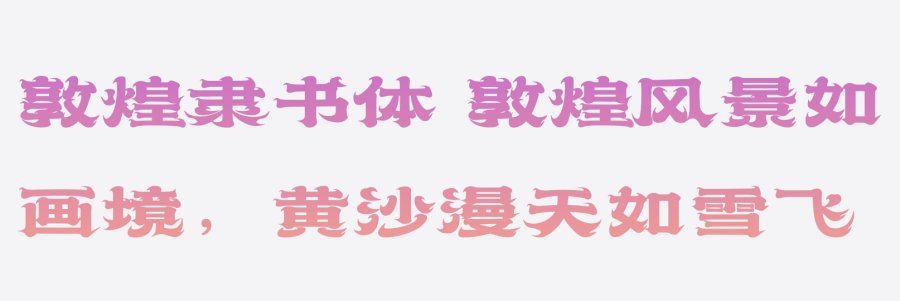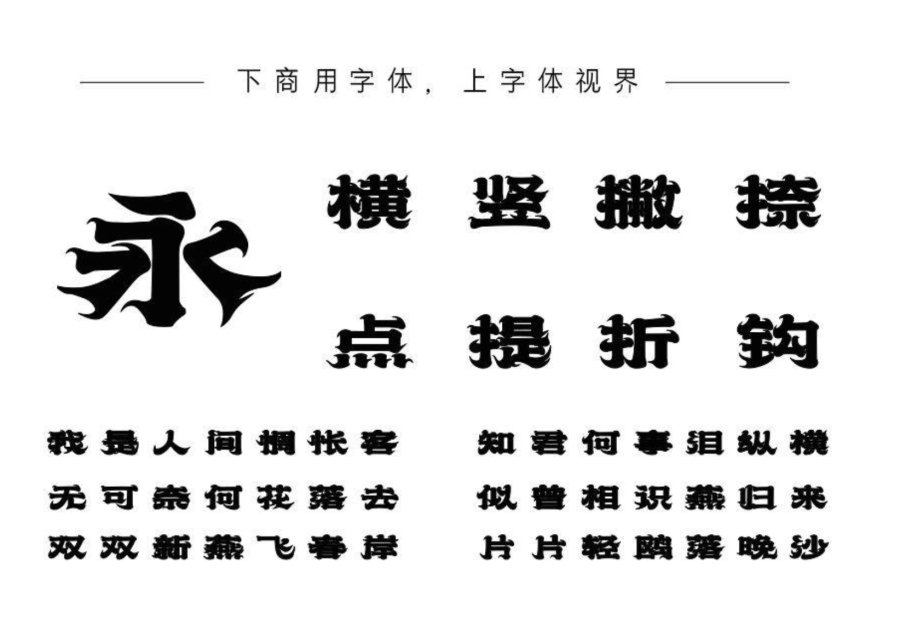
上首敦煌隶书体的灵感源于敦煌飞天,一种在壁画中展现飞舞仙姿的神奇存在。字体整体采用敦煌壁画的艺术特点,每一笔仿佛飞天的巾带,脱离尘世束缚,翩然飞舞在纸上。横竖笔画交错,仿若翩跹的仙者,动态有力,又不失轻盈。其气度宏大豪迈,展现出壮阔恢弘的艺术氛围。
隶书体本就是汉字书法中的一大奇迹,而敦煌隶书体更是在传承中融汇了西域文化的瑰宝,使得这一艺术形式更加独特而美妙。在书写的过程中,仿佛能感受到那遥远年代的辉煌,那灿烂岁月的飞扬感动。
上首敦煌隶书体,不仅是一种艺术的传承与延续,更是一种精神的抒发与追求。让我们随着这些飞天的字形,穿越时空,在历史的长河中领略那飞天之境的艺术魅力。